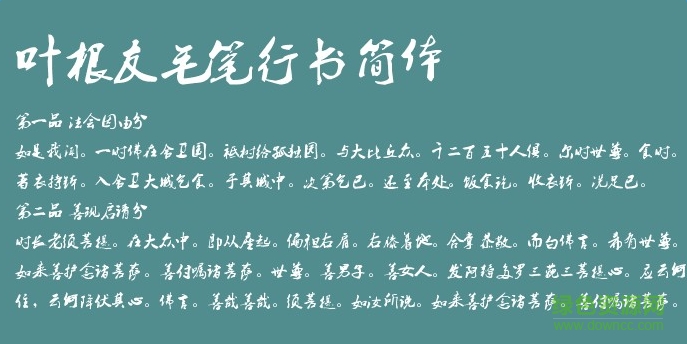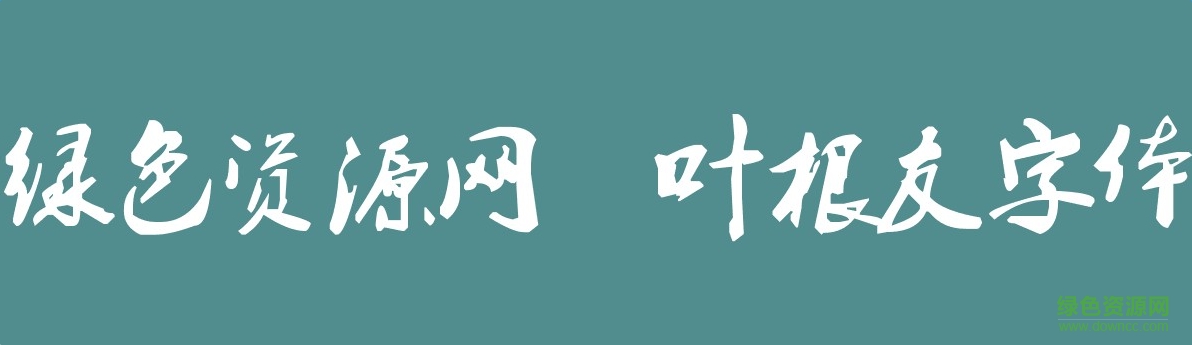
葉根友行書簡(jiǎn)體字體
葉根友毛筆行書簡(jiǎn)體字體是由中國(guó)書法奇人,五筆同書世界首創(chuàng)者,連筆空心字吉尼斯世界紀(jì)錄保持者葉根友先生親自書寫的一款字體,是葉根友先生平時(shí)書寫最多的一種,也是最為實(shí)用的風(fēng)格。字體大方,流暢。歡迎下載!
葉根友毛筆行書簡(jiǎn)體字體